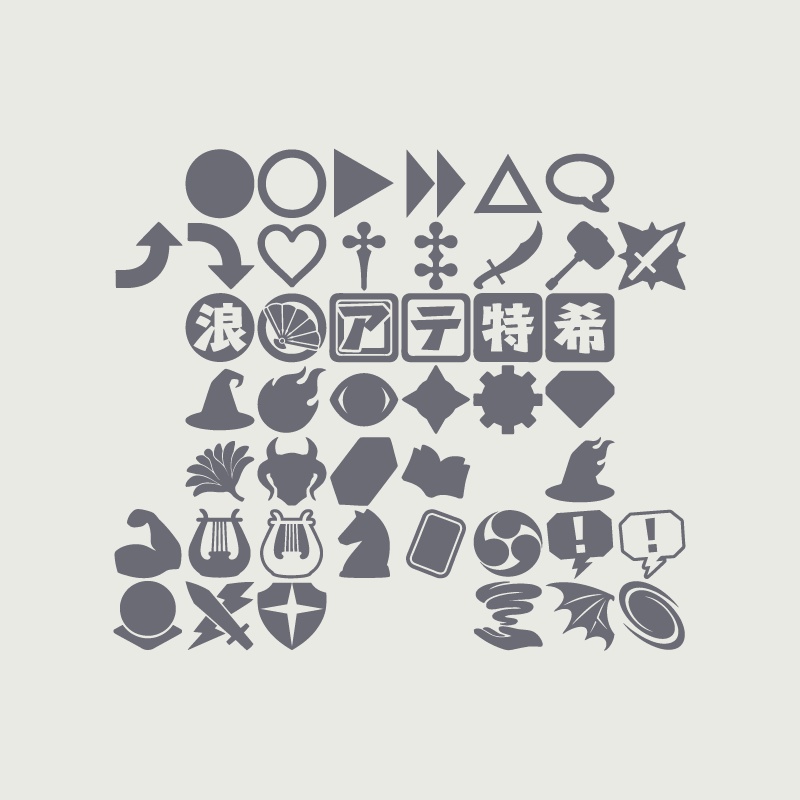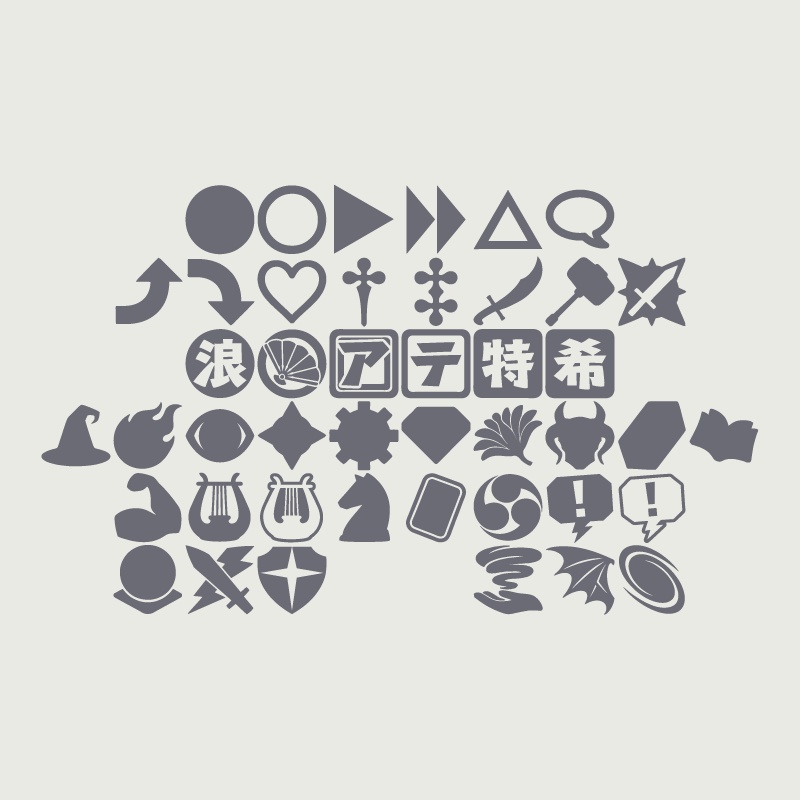
ソード・ワールド2.5シンボルフォント プラネスセミオチカ 巡涯学派記号目録
ソード・ワールド2.5(部分的に2.0も)作品内で使用されている記号やシンボルなどを、アレンジを加えつつまとめたフォントデータです。 セッション素材や同人作品など、ソード・ワールド関連の創作などに、有償/無償問わず無料でご利用いただけます。 収録文字の割り当て・入力方法については、以下のリンク先をご確認ください。 https://organontorah.wixsite.com/planes/font ご利用いただく上でのお願いは主に2つ。TRPGライツ事務局様の「二次創作活動のガイドライン」に従っていただく事と、有償作品へ使用いただく際はクレジットの記載をいただく事です。 詳細につきまして、同封しているテキストファイルに記載しております。ご確認のうえでご利用いただくよう、お願いいたします。 本作は、「著:北沢慶/グループSNE、KADOKAWA」が権利を有する『ソード・ワールド2.0/2.5』の二次創作作品です。
v2.0 2026/03/19 呪言魔法のシンボルを追加しました